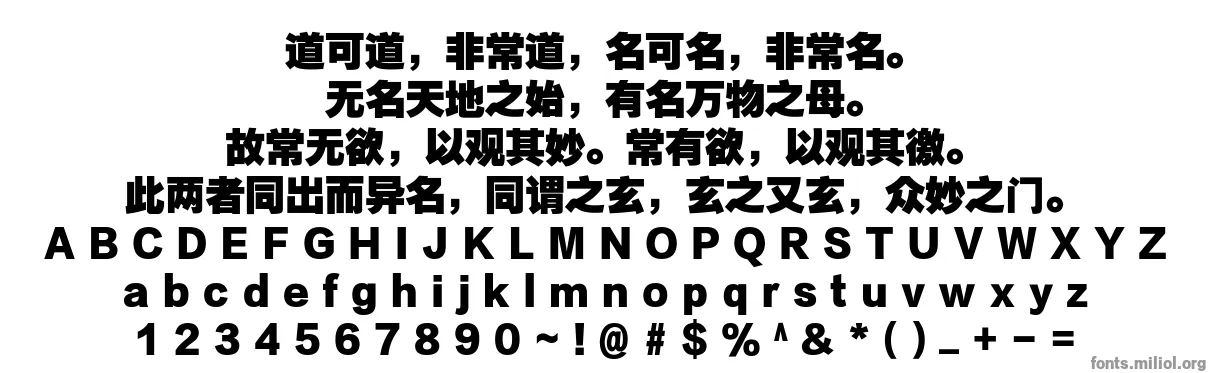
方正超粗黑_GBK (FZChaoCuHei-M10) (FZCCHK--GBK1-0) 字体下载
《方正超粗黑_GBK (FZChaoCuHei-M10) (FZCCHK--GBK1-0) 字体下载》是一款极具视觉冲击力的中文字体,适用于标题、广告、海报等需要突出显示的场景。其粗犷的笔画和饱满的结构,赋予了文字强烈的表现力,能够迅速吸引观众的注意力。该字体支持GBK编码,涵盖了丰富的汉字字符集,适用于多种设计需求。方正超粗黑_GBK字体不仅在设计领域广受欢迎,也在印刷、出版等行业中得到了广泛应用。无论是商业宣传还是艺术创作,这款字体都能为作品增添独特的视觉魅力。